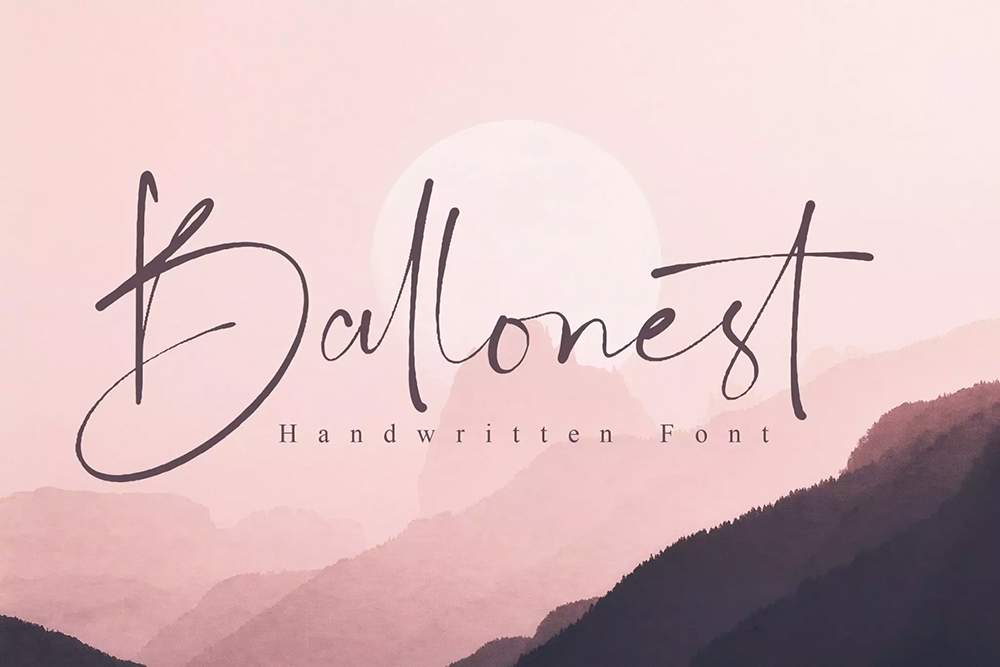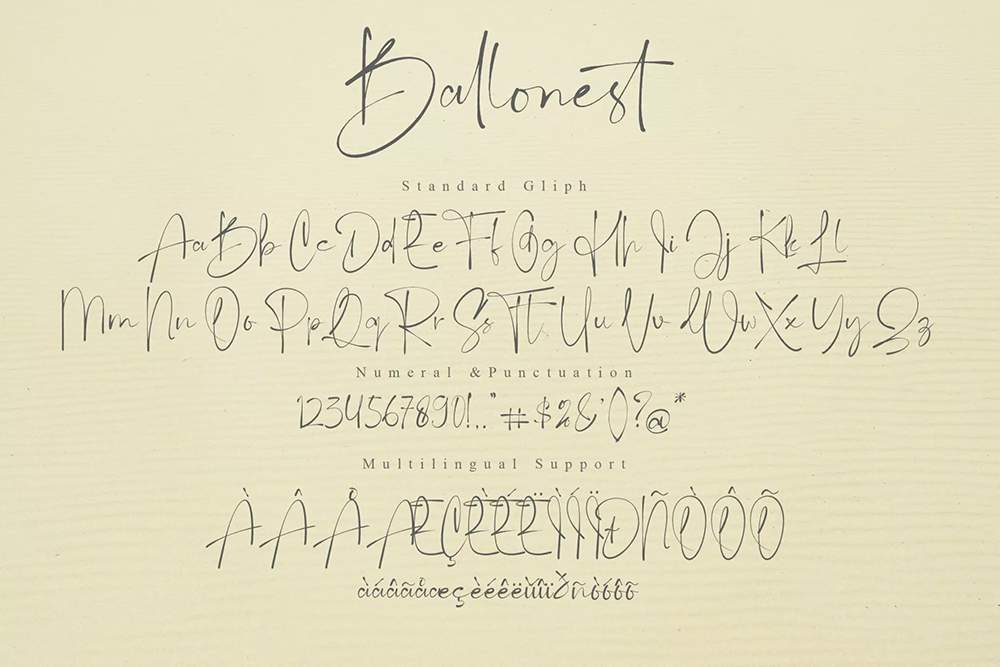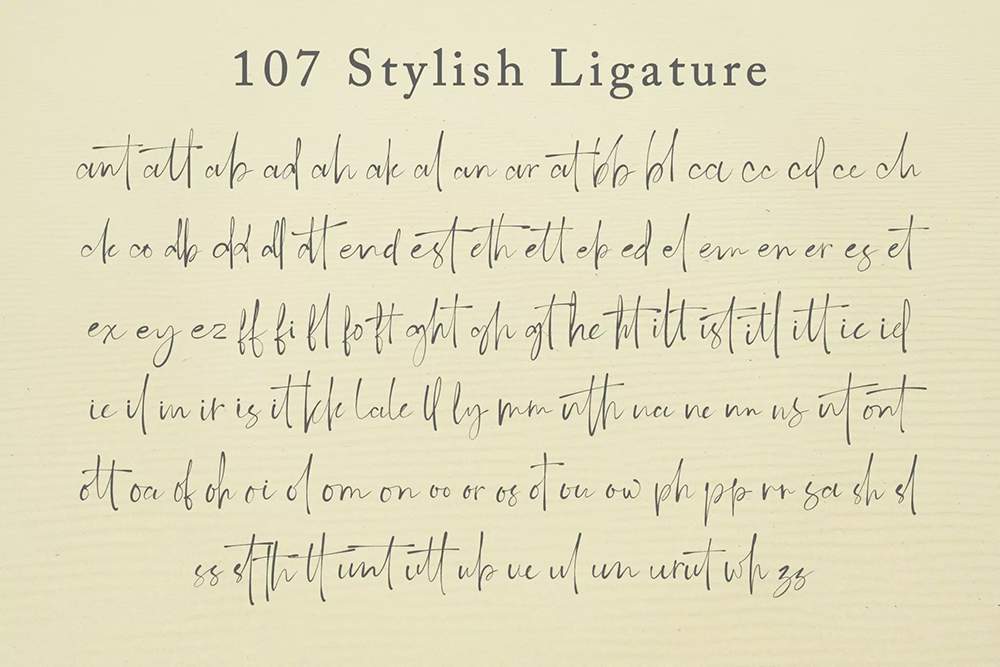
فونت پرمیوم و انگلیسی Ballonest Font یک فونت دستنویس با ظاهری شیک، زیبا و طبیعی که دارای مجموعهای کامل از کاراکترهای A تا Z با 107 لیگاتور…
فونت پرمیوم و انگلیسی Ballonest Font یک فونت دستنویس با ظاهری شیک، زیبا و طبیعی که دارای مجموعهای کامل از کاراکترهای A تا Z با 107 لیگاتور شیک است. این فونت حس اصیل و دستخط زیبایی دارد. با جدیت، دقت و احساس ساخته شده است. Ballonest برای عکاسی، واترمارک، پستهای رسانههای اجتماعی، تبلیغات، لوگو و برندسازی، دعوتنامه، طراحی محصول، برچسب، لوازم التحریر، طراحی عروسی، بستهبندی محصول، رویدادهای ویژه یا هر چیزی که به سلیقه دستنویس نیاز دارد، عالی خواهد بود. دانلود شما شامل فایلهای زیر خواهد بود.
مزایای استفاده از فونت لاتین Ballonest چیست؟